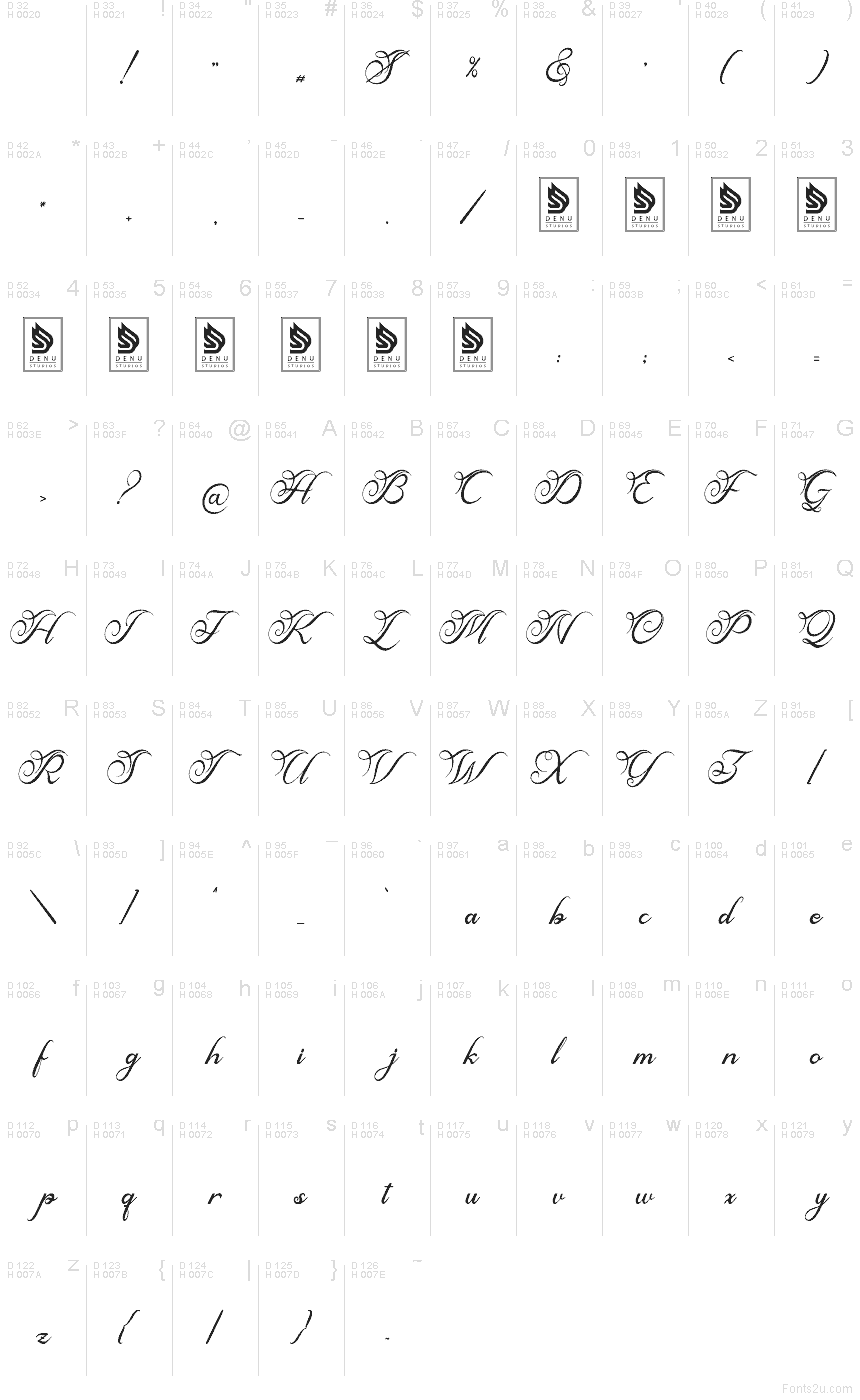
Mutasha Wonderal de Denustudios es una tipografía caligráfica moderna y gratuita que evoca la ligereza de las escrituras formales para bodas. Sus letras destacan por trazos largos y fluidos similares a cintas, acompañados de una dramática floritura inicial, mientras que el resto de la palabra mantiene un ritmo más relajado y natural, logrando un equilibrio elegante sin perder la frescura.
Es perfecta para invitaciones de boda, packaging de belleza, logotipos de boutiques, portadas de libros y títulos en redes sociales donde unas pocas palabras marcan el estilo. Al ser una fuente gratuita, también funciona de maravilla para monogramas, branding con un toque personal y titulares cortos, ya que sus curvas extensas necesitan un poco de espacio para lucirse.